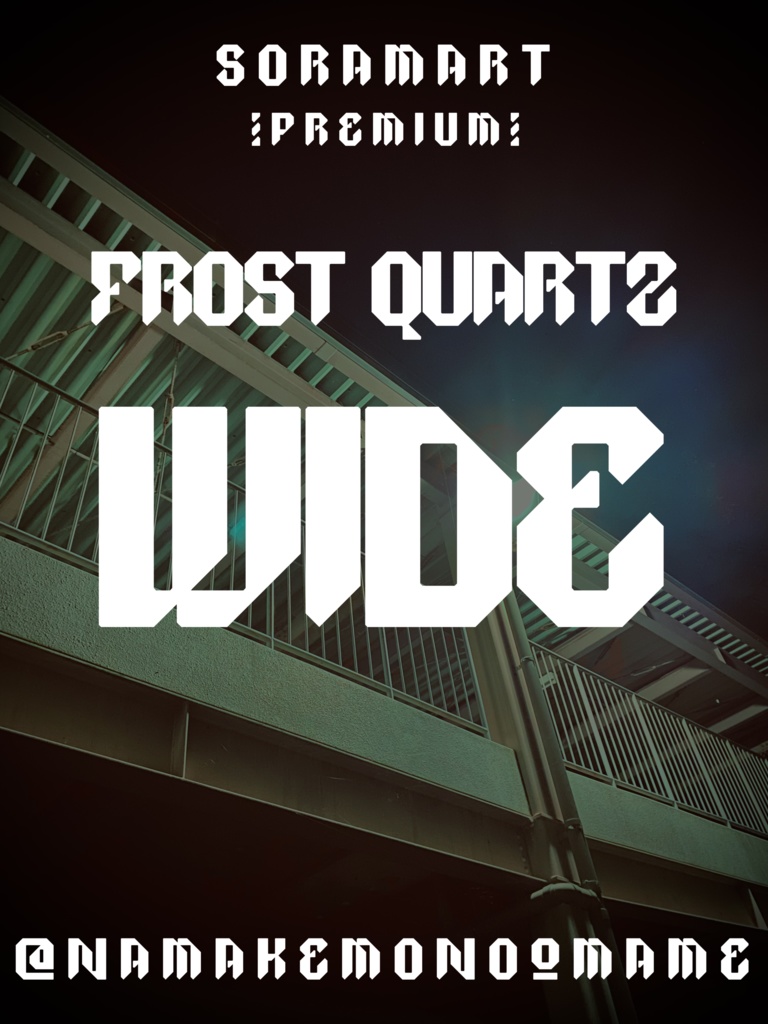
そらマートフォントデータ”Frost Quartz Wide”ダウンロード商品¥ 2,500カートに入れるギフトとして贈る「ギフトとして贈る」とは氷をイメージした斜線モチーフのフォントを太文字にアレンジした "Frost Quartz Wide" です。 「TrueTypeフォントファイル」という形式です。 ダウンロードした後、Zipファイル内のデータをインストールしてお使いください。 このフォントは商用利用可となっております。 お客様の制作・創作活動のお役に立てれば幸いです。 ※使用上の注意事項などは、添付のReadmeをお読みください。 ※このフォントは、有料販売専用商品です。そらマートFANBOX開設中フォント・書体フォントデータ”Popcorn Tab Plasma”そらマート¥ 2,500フォント・書体フォントデータ”Popcorn Tab Heavy”そらマート¥ 0フォント・書体フォントデータ”Popcorn Tab”そらマート¥ 0フォント・書体フォントデータ”Tetra Pixel Dash”そらマート¥ 2,500フォント・書体フォントデータ”Tetra Pixel Fluid”そらマート¥ 2,500フォント・書体フォントデータ”Tetra Pixel”そらマート¥ 2,500フォント・書体フォントデータ”Neon-Lit Empire Long”そらマート¥ 2,500フォント・書体フォントデータ”Neon-Lit Empire”そらマート¥ 2,500フォント・書体フォントデータ”Jumping Meteor Drop”そらマート¥ 2,500フォント・書体フォントデータ”Jumping Meteor Wide”そらマート¥ 2,500フォント・書体フォントデータ”Jumping Meteor”そらマート¥ 2,500フォント・書体フォントデータ”Ragtime Key Tall”そらマート¥ 2,500フォント・書体フォントデータ”Ragtime Key Bold”そらマート¥ 2,500フォント・書体フォントデータ”Ragtime Key”そらマート¥ 2,500フォント・書体フォントデータ”Cocoon Bullet Emerge”そらマート¥ 2,500フォント・書体フォントデータ”Cocoon Bullet Slug”そらマート¥ 2,500フォント・書体フォントデータ”Cocoon Bullet”そらマート¥ 2,500フォント・書体フォントデータ”Frost Quartz LL”そらマート¥ 2,500フォント・書体フォントデータ”Frost Quartz”そらマート¥ 2,500フォント・書体フォントデータ”Highway Surfer Loud”そらマート¥ 2,500もっと見る